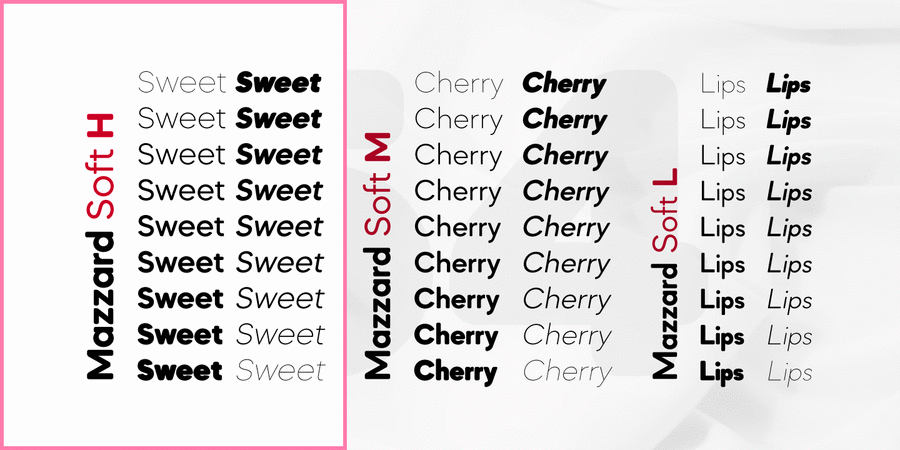
Опис гарнітури Mazzard Soft H – це частина шрифтового сімейства Mazzard Soft, котре є версією з заокругленими кутами суперсімейства Mazzard. У цій версії є ще два геометричних гротеска, які різняться висотою рядкових знаків (M і L).
Шрифт має широкий спектр підтримки мов, зокрема кирилицю, та пропонує великій вибір альтернативних гліфів.
Шрифт розробив Олег Ліщук в 2019 році.
Особливості сімейства шрифтів Mazzard Soft HХіт десятиліття:
Асоціації з сімейством шрифтів Mazzard Soft HОсобистість і характер гарнітури:
елементарний, мінімалістичний, точний, рівний, статичний, логічний, лаконічний, стійкий, штучний, холодний, міський, чистий, сучасний, тонкий, дротяний, легкий, прохолодний, ясний, невагомий, прозорий, крихкий, модний, худий, неоновий, круглий, М'який, свіжий, пластмасовий, гладенький, стабільний, Простий, нейтральний, урбаністичний, зрозумілий, примітивний, домашній, формальний, прагматичний, практичний, доступний, впевнений, машинний, сильний, самостійний, переконливий, обов'язковий, міцний, важливий, мотивуючий, крутий, залізничний, амбітний, добротний, спекотний, потужний, товстий, значний, яскравий, помітний, важкий, щільний, тісний, активний, гучний, сміливий, гумовий
дизайн, лосьйон, туалетна вода, мода, АСМР, небо, прилад, Місто, наука, технології, інновації, девайс, гаджет, магазин, одяг, взуття, канцтовари, олівці, шампунь, косметика, хімія, математика, код, коворкінг, меблі, інтер'єр, дім, вода, техніка, робот, фломастери, анімація, мультфільм, гра, їжа, шоу, телебачення, інструмент, тренажери, ремонт, новини, енергетика, прес, залізниця, спальня, родина, іграшка, подушка, підгузок Гарнітура асоціюється з віком: